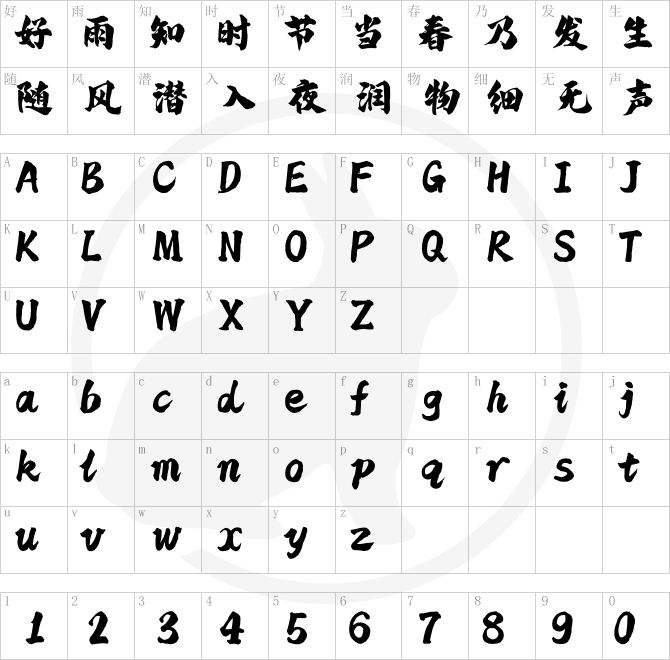
Aa阳关曲
Aa阳关曲,这款字体结构工整、笔画清晰,兼顾美观与易读性,适用于标题、正文、海报、包装、LOGO 等多种场景。字形优雅稳定,风格百搭耐看,适配日常排版与创意设计,让文字呈现更舒适、更具质感。Aa阳关曲一笔一画,皆是细节,以均衡的比例、流畅的线条打造舒适视觉体验,字形端正大气,风格简约现代。无论是商业设计、品牌宣传还是日常排版,都能轻松驾驭,让文字更有格调与力量。Aa阳关曲字体下载。